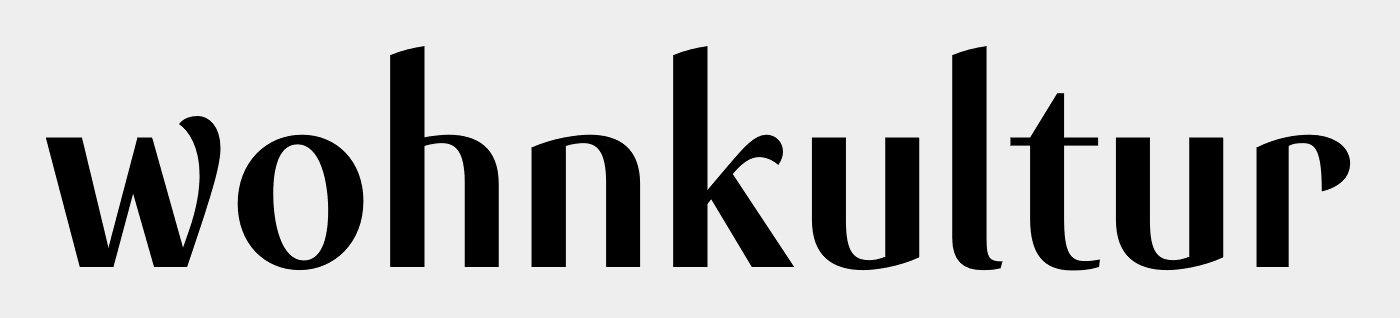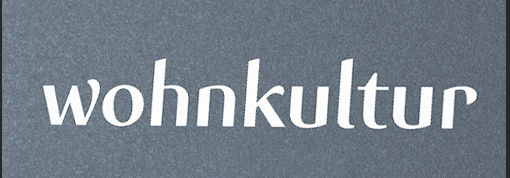
Suche diese besondere Schrift mit "Kringel" (wohnkultur)
ich suche diese für mich besondere Schrift die ich leider in keinen der typischen Portalen wie Fonts, Adobe, etc. finde.
Der Screenshot stammt von einem Entwurf, der leider nicht mehr nachzuvollziehen ist. Ich bitte um Unterstützung. Vielen Dank im Vorfeld.